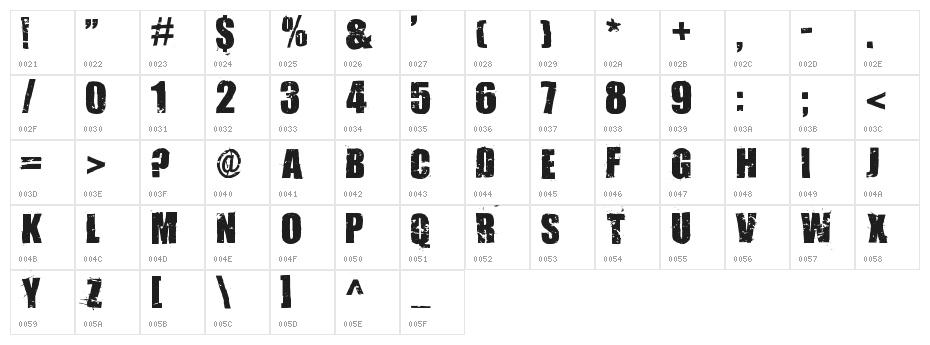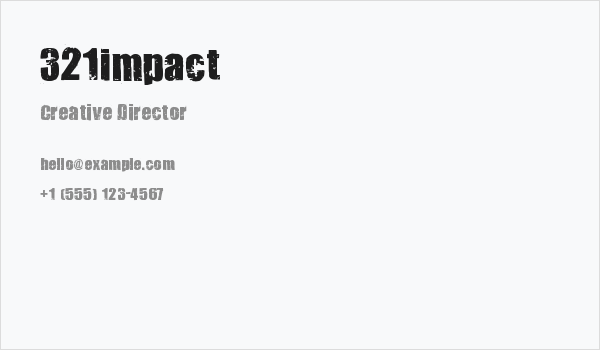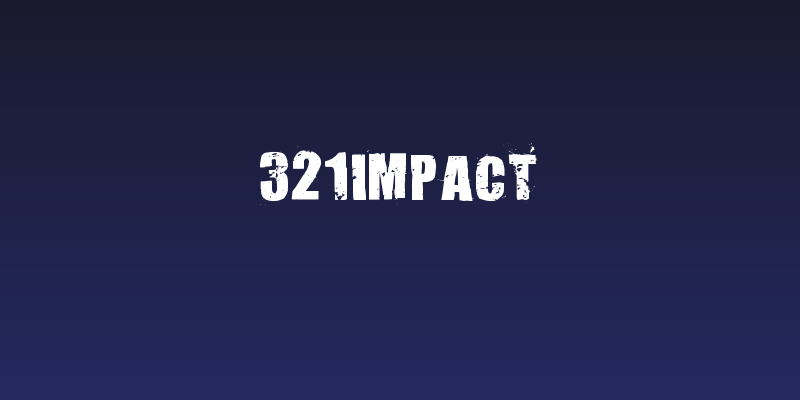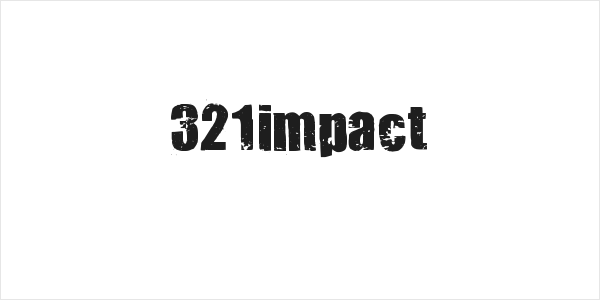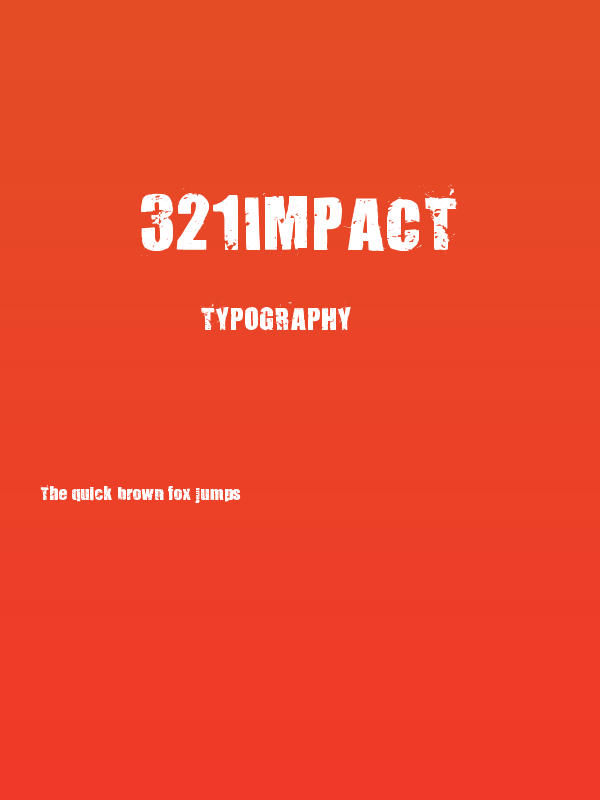
321impact Font
✎ Distorted Eroded
| Kategorien | Distorted Eroded |
| Gesamtstil | Vintage |
| Vorgeschlagene Projekte | Ideal for posters, album covers, branding, and any design needing a bold, vintage look. |